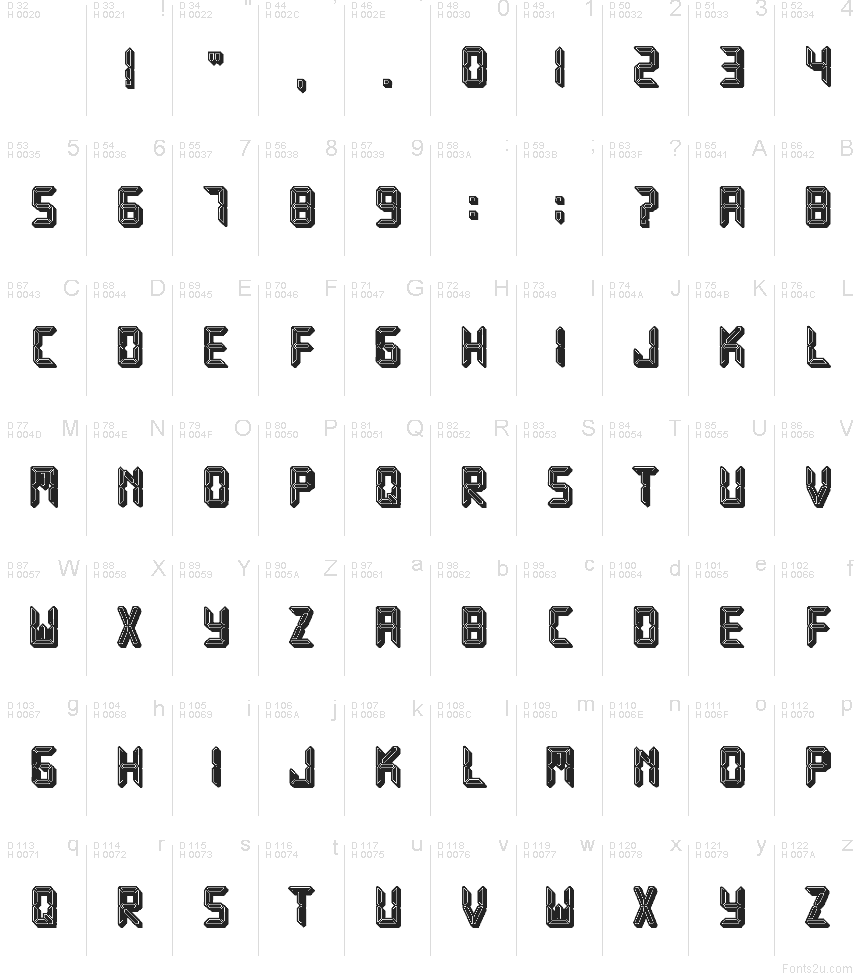
Fake Hope Filled, de Vladimir Nikolic, es una tipografía display gratuita de ciencia ficción con letras de bordes afilados y una hendidura 3D facetada que recorre las mayúsculas. Sus formas parecen talladas en metal, con uniones diagonales y líneas incisas que le dan a la tipografía un ritmo futurista y contundente, sin que se sienta como un simple adorno.
Encaja perfectamente en logotipos de videojuegos, pósteres de estilo synthwave, branding para eventos tecnológicos, títulos de crédito y encabezados breves donde se busca una tipografía gratuita que aporte profundidad por sí sola. Úsela cuando desee que las letras tengan un mayor protagonismo visual, especialmente en titulares compactos o monogramas que se vean potenciados por su silueta angular de corte industrial.
Fake Hope está disponible en versiones Regular y Filled.